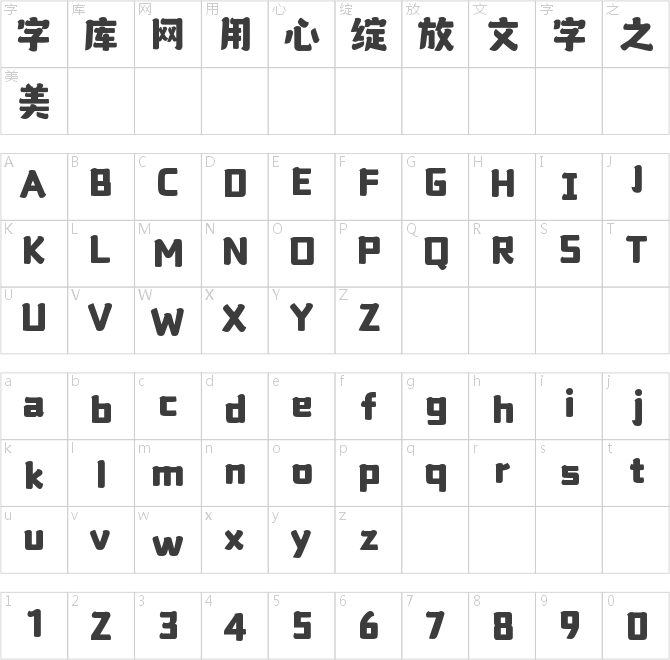
山海萤火虫,是一款卡通风字体,包含简繁汉字9169个。字体童趣可爱,结构多变灵动,字形活泼清新,造型生动有趣,具有灵活的适用性,天真俏皮又不失时尚感。
山海萤火虫W字体字库是一款让人赏心悦目、百看不厌的中文字体,适合各类广告和产品包装设计应用,字体大小5.49MB,格式为ttf字体,上传用户是山海字库,作者/版权方为山海字库